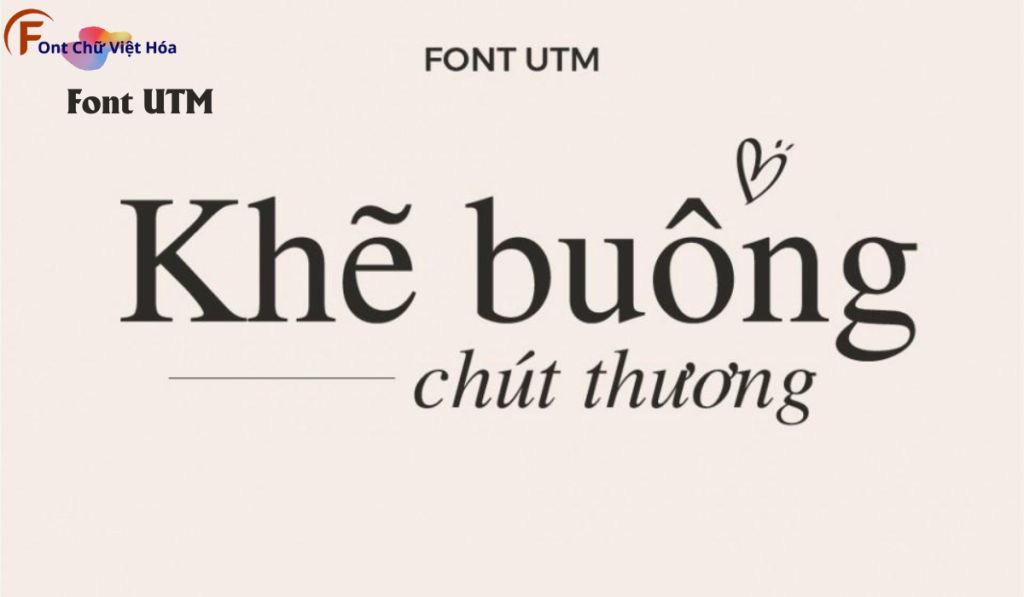
Font UTM Times Việt Hóa
Tác giả: UTM Times
Bộ Font: UTM
Phân loại: cổ điển
Kiểu chữ: có chân
Độ dày: thường, nghiêng
Font UTM Times Việt Hóa là một font chữ có chân cổ điển, thuộc bộ font UTM. Được thiết kế với mục tiêu mang lại sự truyền thống và chuyên nghiệp, font này lý tưởng cho các dự án thiết kế như báo chí, sách giáo khoa, và tài liệu học thuật. Với các nét chữ rõ ràng và độ dày đều đặn, Font UTM Times Việt Hóa không chỉ dễ đọc mà còn tạo cảm giác nghiêm túc và đáng tin cậy. Việc Việt hóa font giúp người dùng dễ dàng tích hợp vào các thiết kế tiếng Việt, mang lại sự tiện lợi và nâng cao tính thẩm mỹ.